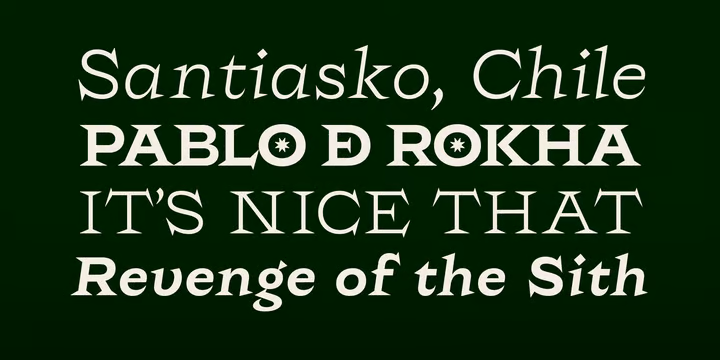
Rokha Font Family
Description de Rokha Font Family
Rokha est une police à empattement compensé avec 5 graisses plus des obliques. Ses empattements nets ont été inspirés par le classique Copperplate Gothic de Goudy, Rokha donne l’impression que la terre ressemble à de la pierre sculptée, audacieuse et pointue. Les empattements sont exagérés, pointus et forts, cette police exige à tout prix l’attention du spectateur. Les lettres minuscules et majuscules le rendent plus convivial dans différents contextes et lui confèrent une polyvalence supplémentaire. Sa présence saisissante le rend idéal pour l’affichage, les titres, les affiches, les grandes marques et pour attirer l’attention de tout spectateur.